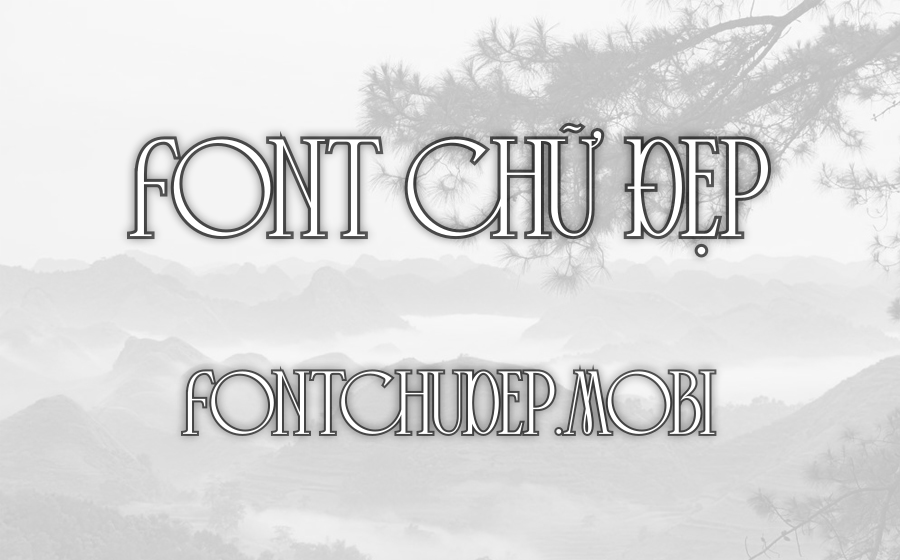
Font SVN Cyrano Việt Hóa
SVN Cyrano
Cyrano là một font chữ serif đầy cá tính và độc đáo mà tôi đã có cơ hội trải nghiệm, do Dharmas Studio tạo nên. Mỗi ký tự của font này được thiết kế với sự tỉ mỉ và chăm chút, làm nổi bật vẻ đẹp thanh lịch và sự chuyên nghiệp. Đáng chú ý, Cyrano đã được Việt hóa bởi Styleno.1 Fonts để hỗ trợ người dùng tiếng Việt, đồng thời còn hỗ trợ nhiều ngôn ngữ khác, điều này giúp font trở nên linh hoạt và có thể sử dụng trên phạm vi toàn cầu. Font này đang được chia sẻ bởi FontChuDep.mobi, khiến việc tìm kiếm và ứng dụng nó trở nên dễ dàng hơn bao giờ hết cho các nhà thiết kế.
Thiết kế của Cyrano nổi bật với các đường nét serif tinh tế, mang đến cái nhìn thanh thoát và hiện đại cho bất kỳ văn bản nào. Đây là lựa chọn lý tưởng cho nhiều ứng dụng khác nhau như thiết kế logo, tiêu đề, nhãn mác, và còn nhiều dự án sáng tạo khác. Nó đặc biệt phù hợp cho các lĩnh vực quảng cáo, nghệ thuật và thiết kế đồ họa, nơi mà sự sáng tạo và tính thẩm mỹ được đặt lên hàng đầu. Trải nghiệm Cyrano thực sự mang lại cảm giác hài lòng và kích thích sự sáng tạo trong các dự án thiết kế của tôi.